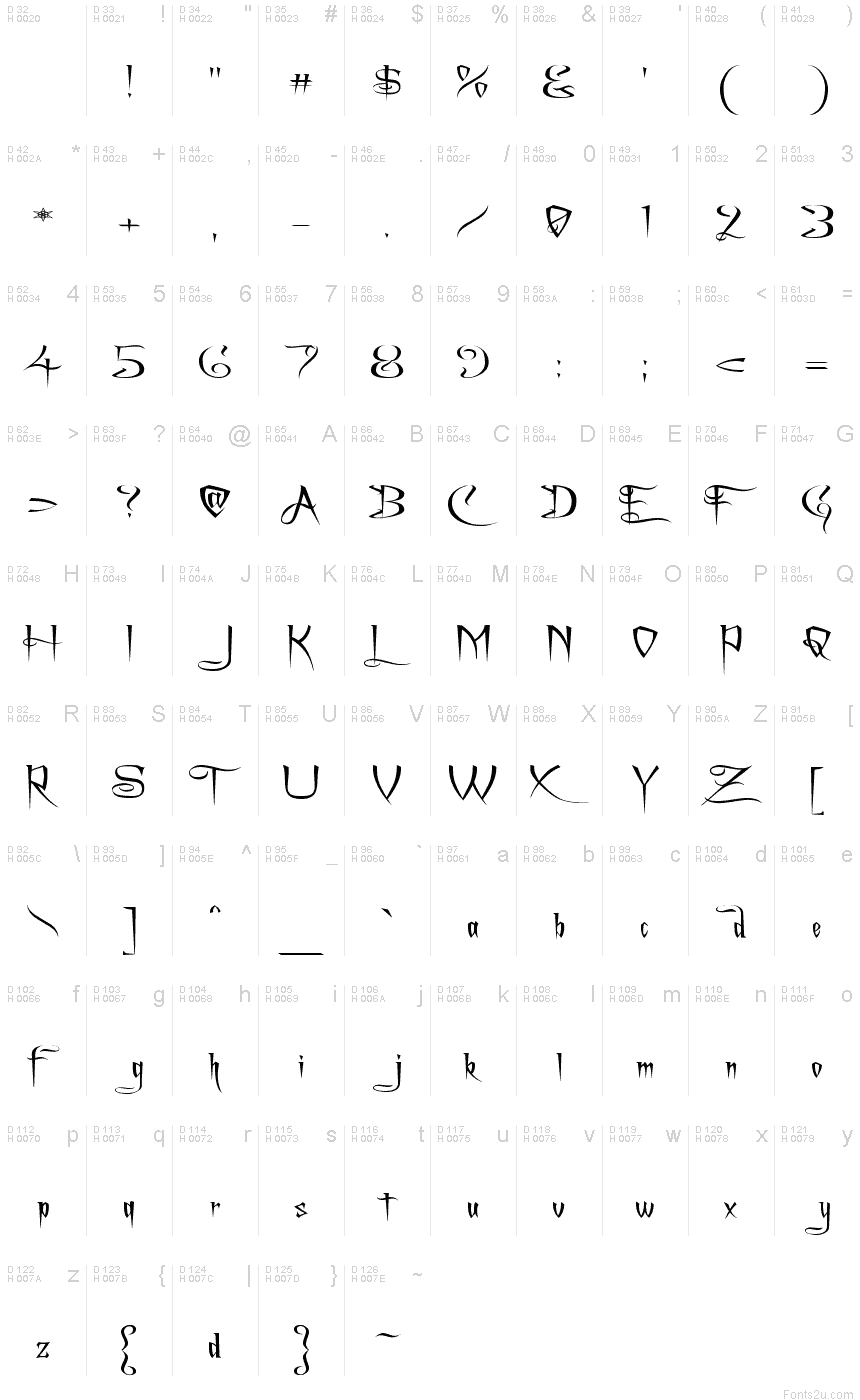
A Charming Font Expanded
A Charming Font Expanded od GeM / A. Höfeld je bezplatné kaligrafické písmo s výrazným nádechem pohádkových příběhů. Dlouhé, zužující se tahy, ostré háčky a ladné křivky dodávají každému slovu nádech magie, jako by bylo napsáno inkoustem ze staré fantasy mapy nebo kouzelnické knihy. Díky rozšířenému rozestupu může každé písmeno dýchat, takže i přes své ozdobné detaily zůstává text čitelný a vizuálně vzdušný, místo aby působil stísněně.
S A Charming Font Expanded získají vaše nadpisy okamžitě kouzelný vzhled – je skvělé pro obálky fantasy knih, listy postav pro RPG, svatební či eventové pozvánky, gotické plakáty, náhledy na YouTube a tematická loga. Toto bezplatné písmo nejvíce vynikne při použití ve velkém měřítku, kdy jeho dramatické křivky a špičaté konce dají plně vyniknout své textuře. Pro hlavní text jej kombinujte s čistým a nenápadným bezpatkovým písmem, aby byl layout vyvážený a lahodil oku.